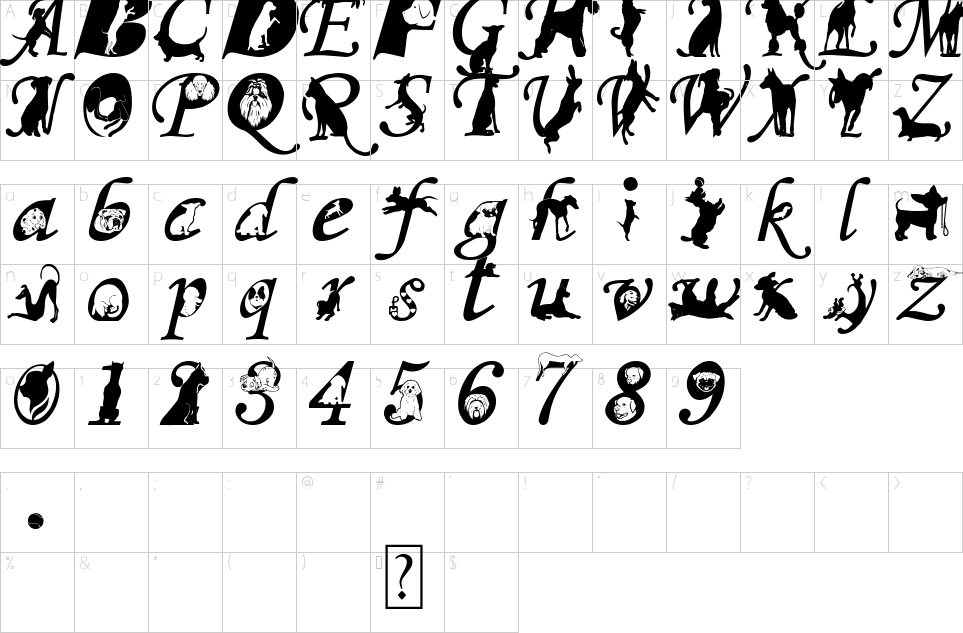
Descubra a graça encantadora do Doggy Dog World Font! Essa simpática fonte, criada por Andrea Steffen, é uma delícia para qualquer projeto digital. Seja para o seu site, aplicativo ou impressão, essa fonte irá dar um toque adorável e único à sua produção. Desenvolvida com um design que lembrará a você de seus petudos preferidos – os cães! Com uma interface elegante e funcional, esta é uma excelente opção para designers e criadores de conteúdo no Windows e Mac. Em apenas 20.178 downloads, já está claro o quanto essa fonte tem conquistado os corações de criativos ao redor do mundo. Descubra por si mesmo o charme encantador do Doggy Dog World Font – seu projeto nunca foi tão divertido.